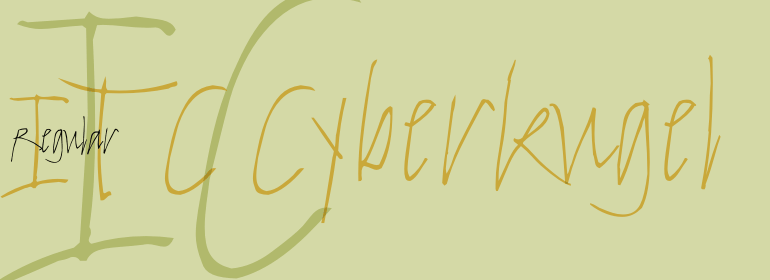
ITC Cyberkugel™
ITC Cyberkugel™,这款字体结构工整、笔画清晰,兼顾美观与易读性,适用于标题、正文、海报、包装、LOGO 等多种场景。字形优雅稳定,风格百搭耐看,适配日常排版与创意设计,让文字呈现更舒适、更具质感。ITC Cyberkugel™一笔一画,皆是细节,以均衡的比例、流畅的线条打造舒适视觉体验,字形端正大气,风格简约现代。无论是商业设计、品牌宣传还是日常排版,都能轻松驾驭,让文字更有格调与力量。ITC Cyberkugel™字体下载。
字体品牌: ITC(Monotype) 设计师:Donaldson,Timothy 字体分类:手写风格字体 字体属性:外文 字符集:Unicode 发布时间: 2018